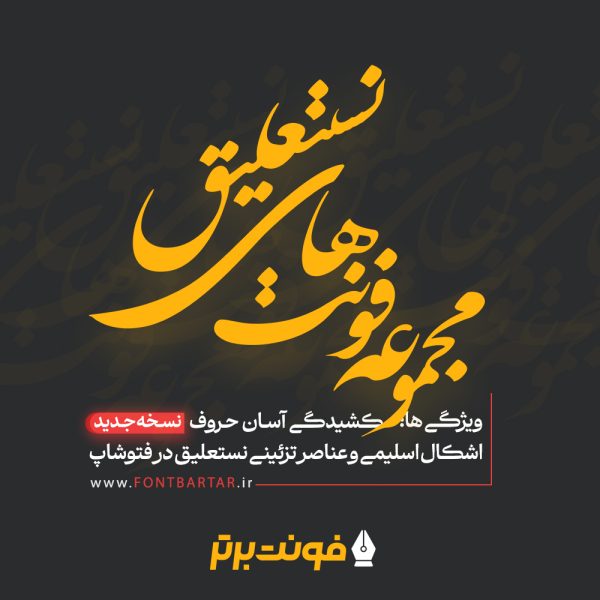
مجموعه فونت های نستعلیق
خط نستعلیق، (متشکل از لغات عربی نسخ و تعلیق) یکی از شیوههای نگارش خط در خوشنویسی فارسی است. این خط در ایران شکل گرفت و بیشتر هم در ایران رواج دارد و خوشنویسان ایرانی بیشتر با این خط به هنرنمایی میپردازند. خط نستعلیق معرف روح و فرهنگ ایرانی است و از آن در نوشتن متنهای ادبی و غیرمذهبی فارسی، اردو و به ندرت عربی استفاده میشود.
فونت نستعلیق نشانهای بارز از طبع و سلیقه زیبایی شناختی ایرانیان است و بیشک زیباترین و ظریفترین خط در میان خطوط اسلامی است تا جایی که آن را بهحق «عروس خطوط اسلامی» لقب دادهاند.
اگر چه میر علی تبریزی (درگذشت ۸۰۳ ه. ق) را واضع این خط معرفی کردهاند اما به نظر میرسد که خط نستعلیق پیش از او نیز وجود داشته و میرعلی تبریزی در سده نهم هجری برای اولین بار خط نستعلیق را تحت قاعده و قوانین خوشنویسی درآورده است و به حدی رسانده که بهصورت خطی مستقل و قابل رقابت با خطوط ششگانه درآید.
در این مجموعه اشکال اسلیمی و عناصر تزئینی نستعلیق در فتوشاپ موجود می باشد که به راحتی می توانید طراحی حرفه ای کنید.